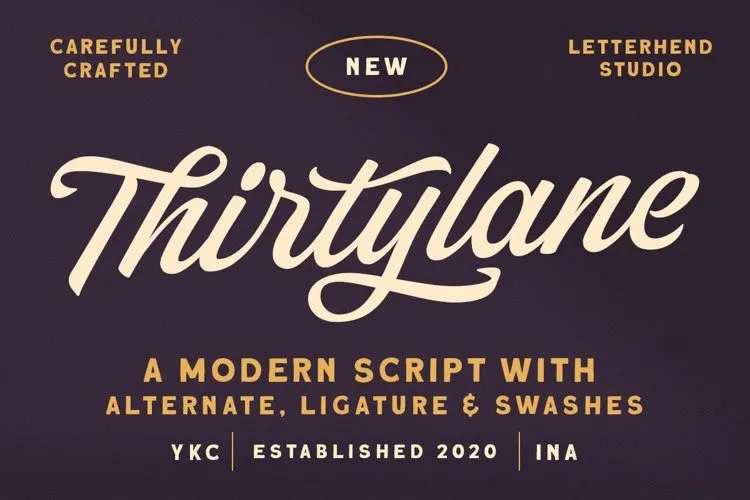
Thirtylane Font
A fonte ‘Thirtylane Font’ é uma tipografia script bold e conectada criada pela Letterhend Studio. Esta fonte possui linhas limpas e curvas suaves misturadas, proporcionando um movimento dramático que se destaca especialmente para aplicações em logotipos e outros formatos formais como convites, rótulos, selos de embalagens, livros, cartões de casamento, embalagens de moda, maquiagem, estaçãoários ou qualquer outra finalidade publicitária. Perfeita para criações criativas que buscam expressar um estilo elegante e moderno, ela é uma opção perfeita para designers em busca de uma fonte atraente e versátil. Composta por linhas fortes e curvas suaves, essa fonte pode ser usada para criar identidades visuais memoráveis e se destacar no design gráfico.